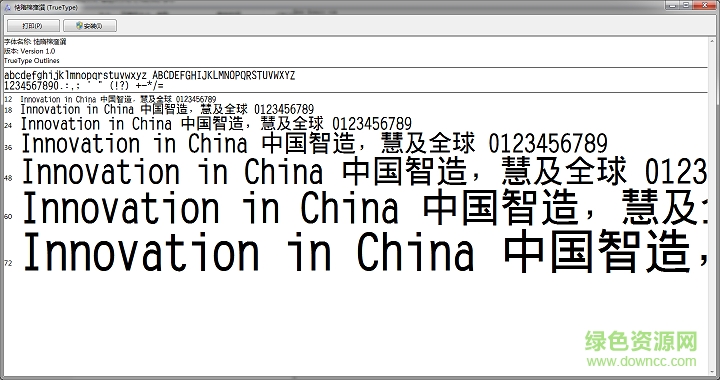
文鼎書苑粗黑字體是一款線條粗曠的粗體字體,這款字體端正大方,字形比較醒目,整體效果十分出色,需要的朋友可以來綠色資源網(wǎng)下載使用喲!
文鼎書苑粗黑字體,字型見方,橫豎比例一致,粗壯穩(wěn)重,醒目突出,適用于報(bào)紙大標(biāo)題及書籍、畫報(bào)的美術(shù)裝幀用字。